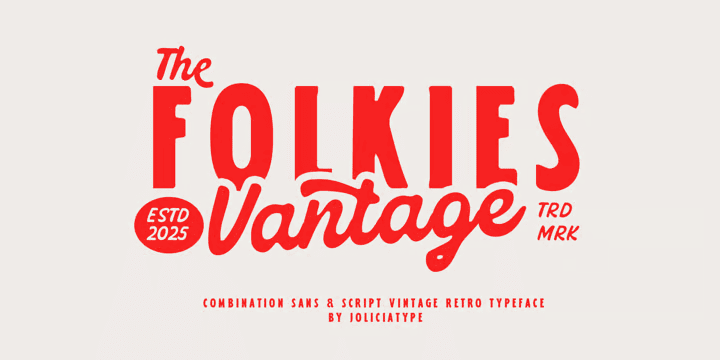
Folkies Vantage
ソフトでヴィンテージ感のあるフォントデュオ。コンデンスで太いウェイトのサンセリフとレタリングスクリプトのデュオで、どちらもアウトラインがややフリーハンドっぽいニュアンスがあって柔らかい。全体的な雰囲気はアメリカンヴィンテージで、スクリプトにちょっとしたスワッシュオルタネートやリガチャーがあるものの、さほどの派手さはなく大人しくてかわいらしい。双方とも1ウェイトのみ。